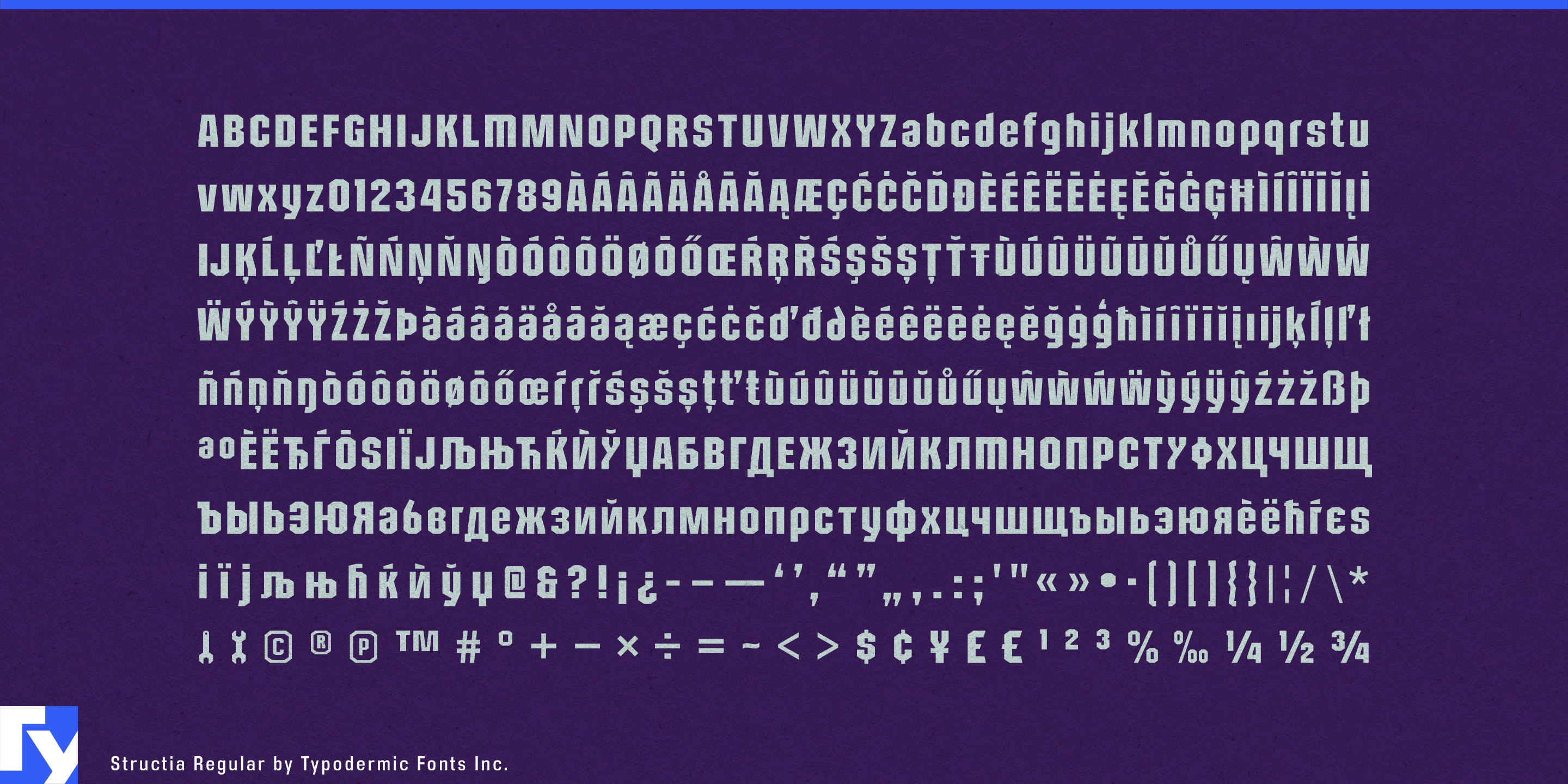
Structia
工業的なディスプレイフォントは、第一印象が強くても用途がすぐに尽きることがあります。八角形を基調にした大文字だけの書体なら機械名やイベント名は扱えても、同じ企画には大小文字を混ぜた見出し、製品群、技術的なグラフィック、よりすっきりした補足資料、ときには摩耗や破損の表現も必要です。Structiaはその広い仕事のために作られました。細身のプロポーション、広く開いたカウンター、角張った造形、実用的な小文字によって、単一の工業的な効果ではなく、機械的なディスプレイシステムになります。
Structia RegularとItalicが中心です。大型機器、産業オートメーション、自律動作する機械、防衛技術、モータースポーツ、業務用工具、高性能機器に合いながら、大文字数文字だけで終わらない開放感があります。製品シリーズ名、機械のバッジ、モデル表示、仕様書の表紙、販売店のグラフィック、機器のデカール、訓練資料のタイトル、展示会の壁面、キャンペーンの見出しに使えます。
Structia Panelは細い内部分割を加え、点検パネル、折り曲げた板金、溶接の継ぎ目、保護用筐体、技術部品の図面を思わせます。無関係な未来風の書体に切り替えずに、先進的な製品ライン、試作システム、技術プレゼンテーション、特別版を区別できます。防衛用ロボット、無人航空機、野外通信、監視機器、産業制御システム、近未来の車両技術には自然に合います。
Structia Warは、同じ構造を物理的な摩耗へ押し進めます。ラリーレイドのグラフィック、モトクロス、オフロード機器、格闘技の販促、頑丈な工具、解体機器、格闘技興行のキャンペーン、車両戦闘ゲームなど、摩耗が一般的なディストピア装飾ではなく題材そのものに属する用途に合います。
三つの処理を、クリーンな機械、設計されたパネル、傷んだ機械という段階として使えます。メーカーなら、日常的な製品識別にRegular、技術的に進んだラインや発売キャンペーンにPanel、劇的なイベントグラフィックや限定の販促資料にWarを使いながら、ファミリーの共通性を保てます。
Structiaはブルータリズム建築の形と機械時代のディスプレイ文字の角張った論理から生まれましたが、その伝統の多くの書体より細く、開放的に描かれています。大きめのカウンター、広い開口部、実用的な小文字によって、短い名前だけでなく見出しや小見出しにも余裕を与えます。強さと機械的な構造を、強度の異なる複数の段階で必要とする企画に特に役立ちます。